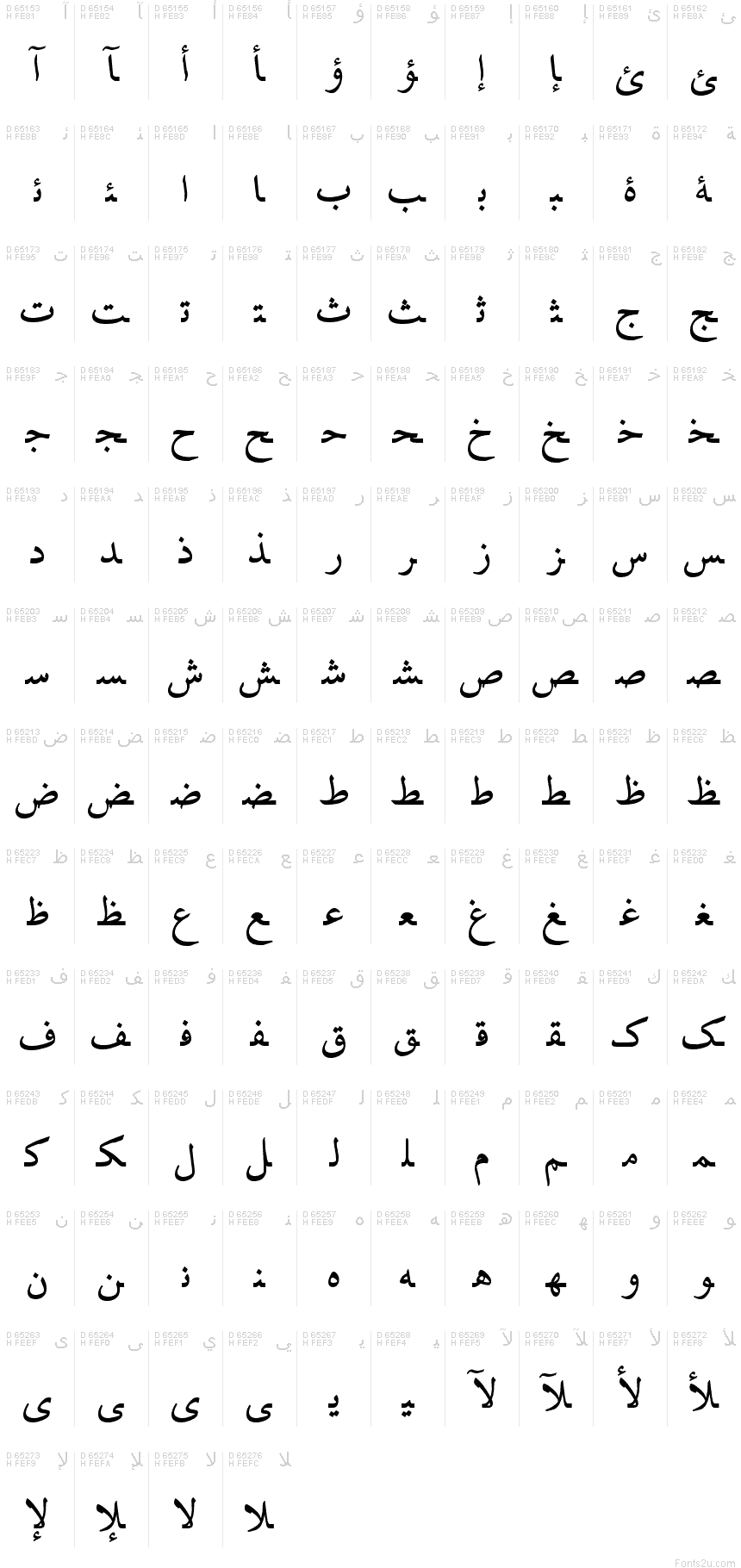
B Baran è un font arabo gratuito di tipo display di Borna Rayaneh, caratterizzato da un ritmo calligrafico compatto e da forme scure e strettamente collegate. Le lettere sembrano costruite con curve audaci e angoli netti, conferendo allo stile una presenza densa, simile a quella di un manifesto, che risulta più grafica che fluida.
È ideale per il branding di packaging alimentari del Medio Oriente, poster di eventi culturali, copertine musicali, cartelli e brevi titoli editoriali dove una silhouette più decisa è preferibile a un testo discreto. Essendo un font gratuito, si adatta bene anche a loghi, grafiche per vetrine e brevi citazioni, specialmente quando cerchi caratteri arabi robusti, compatti ed energici.
B Baran